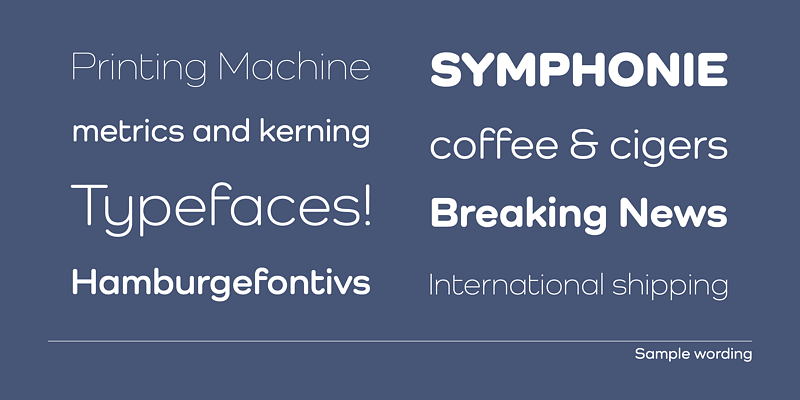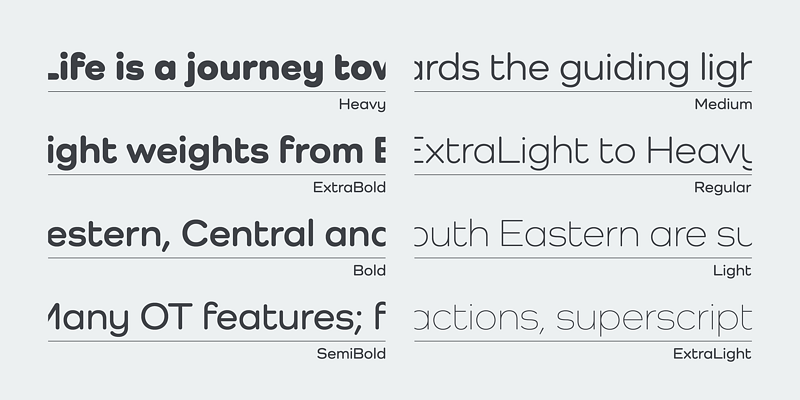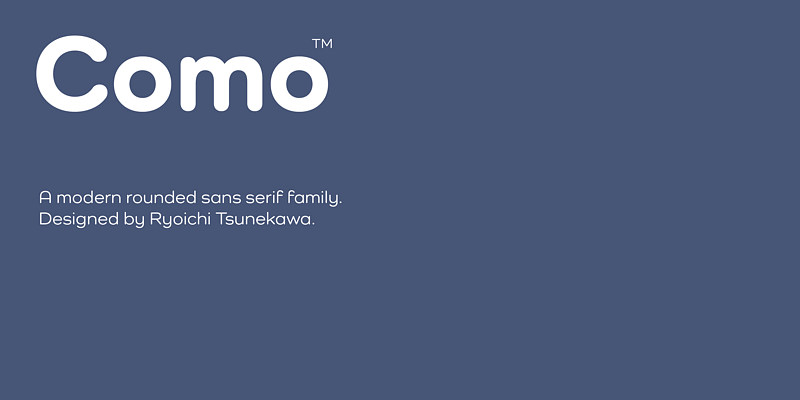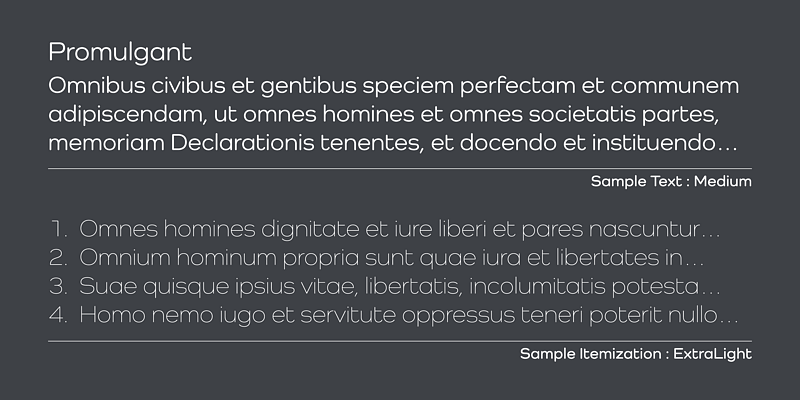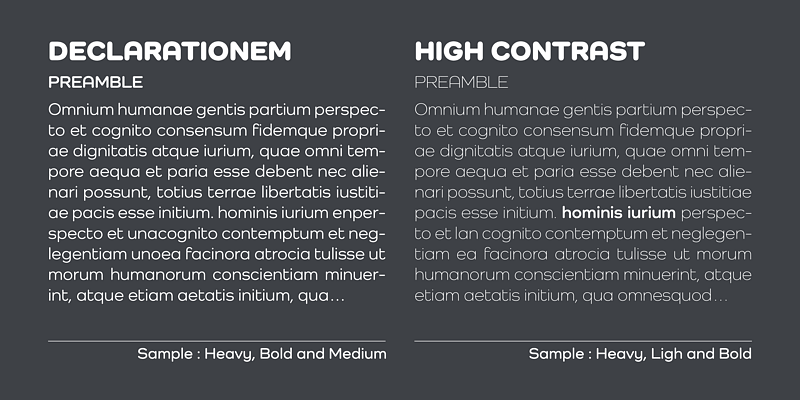
Como ist eine moderne, abgerundete serifenlose Schriftfamilie. Das Grundgerüst ihrer anspruchsvollen Buchstabenform wurde geometrisch gestaltet, wobei die Enden abgerundet wurden.